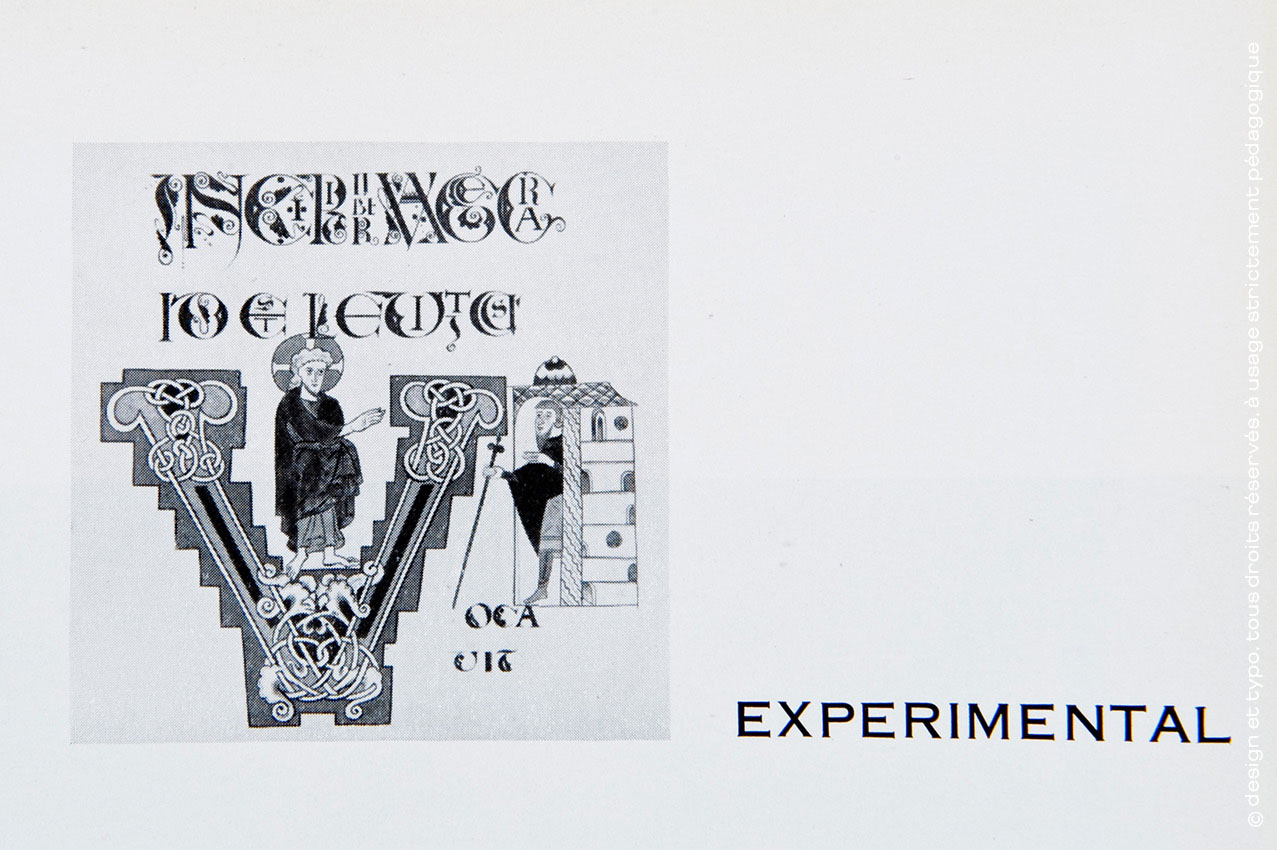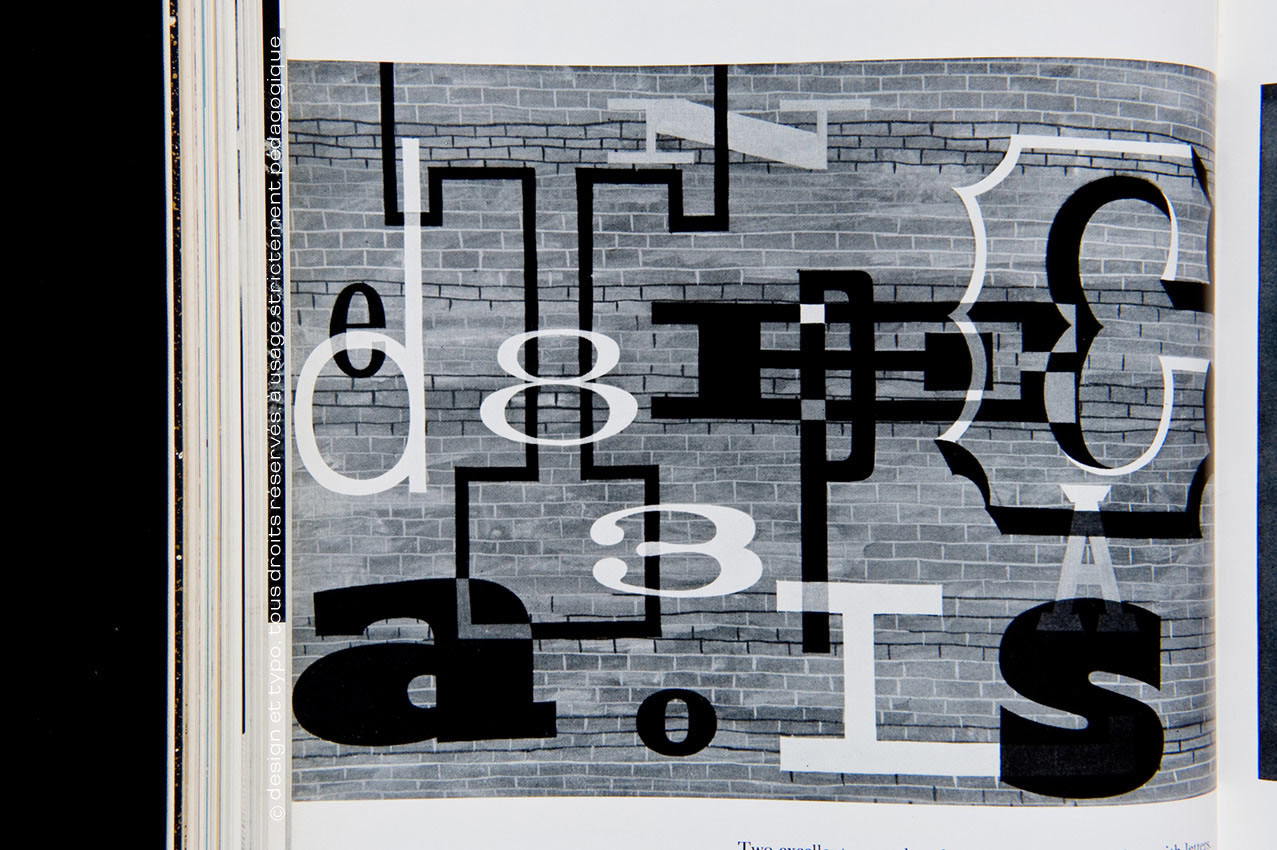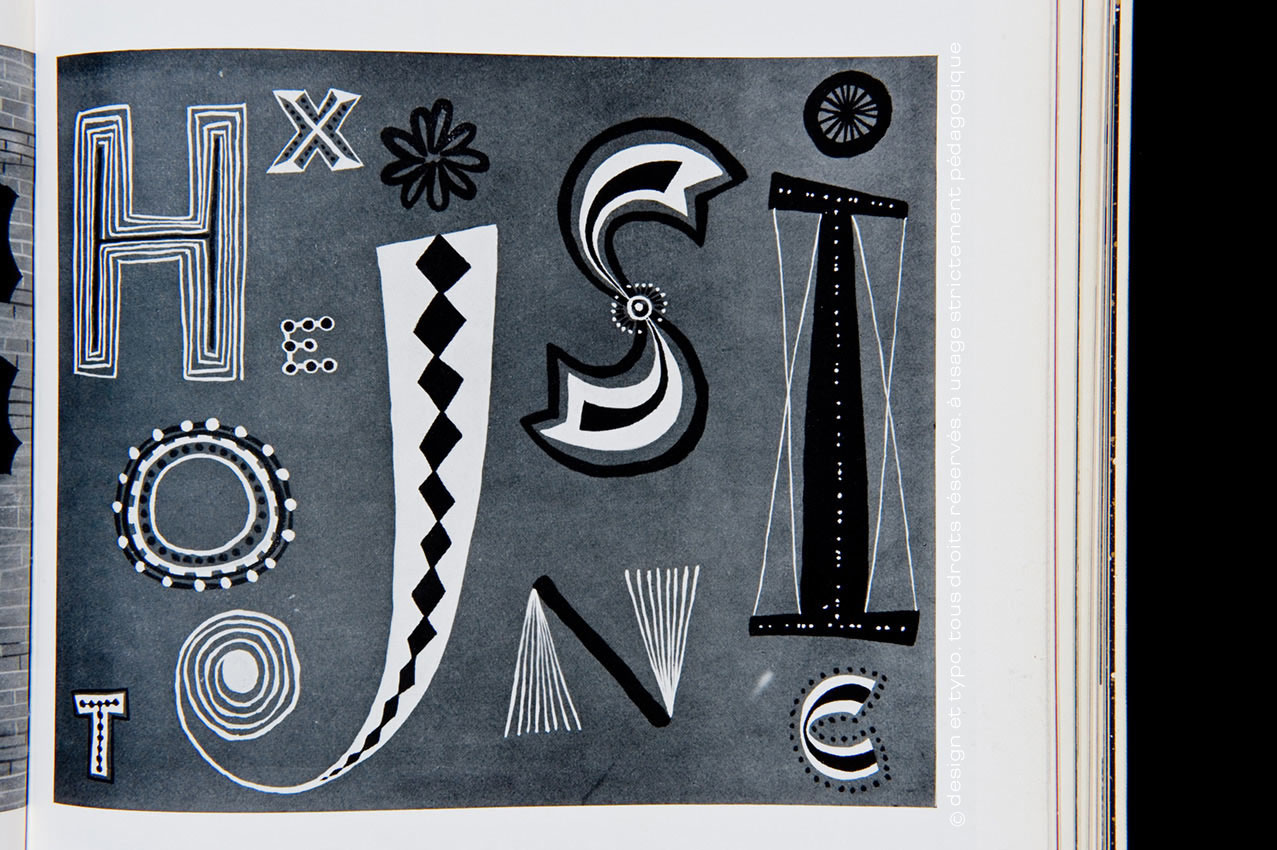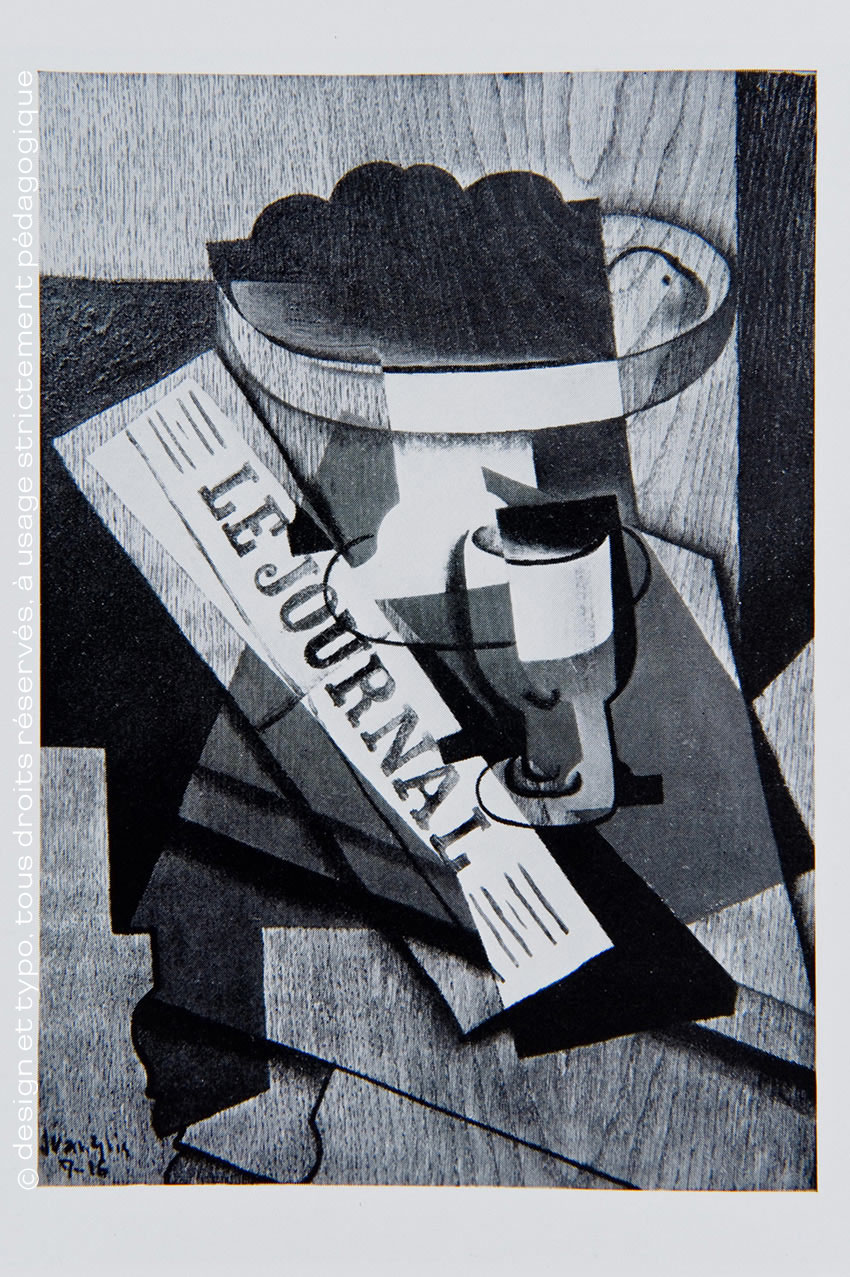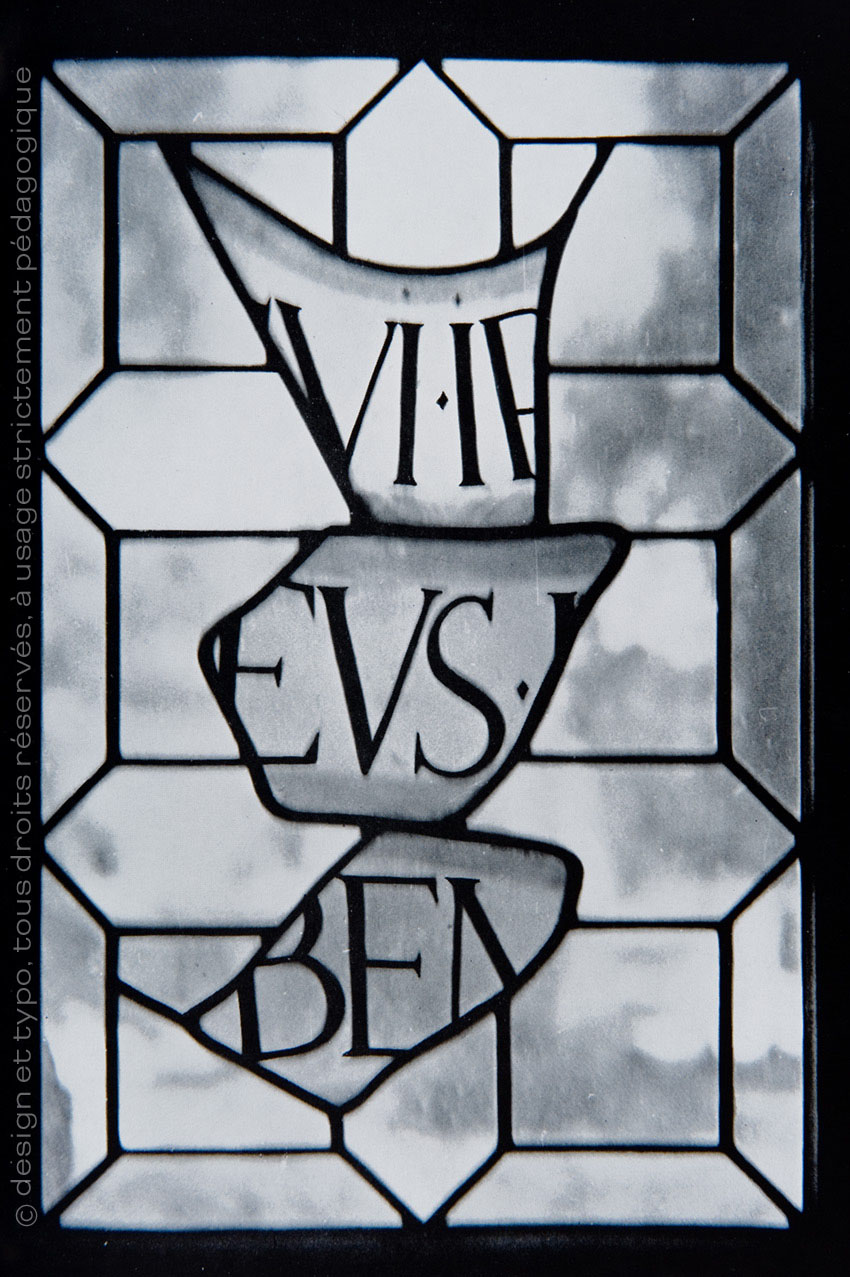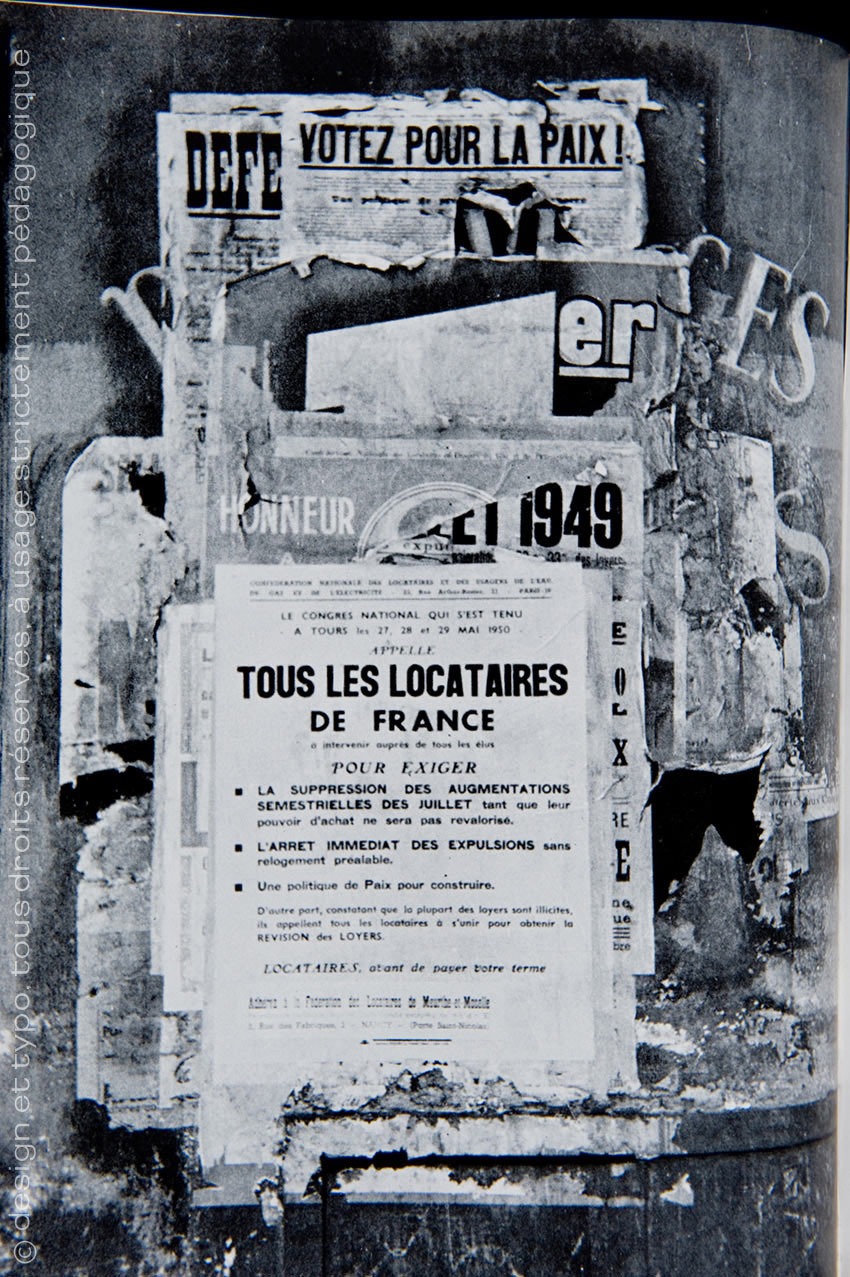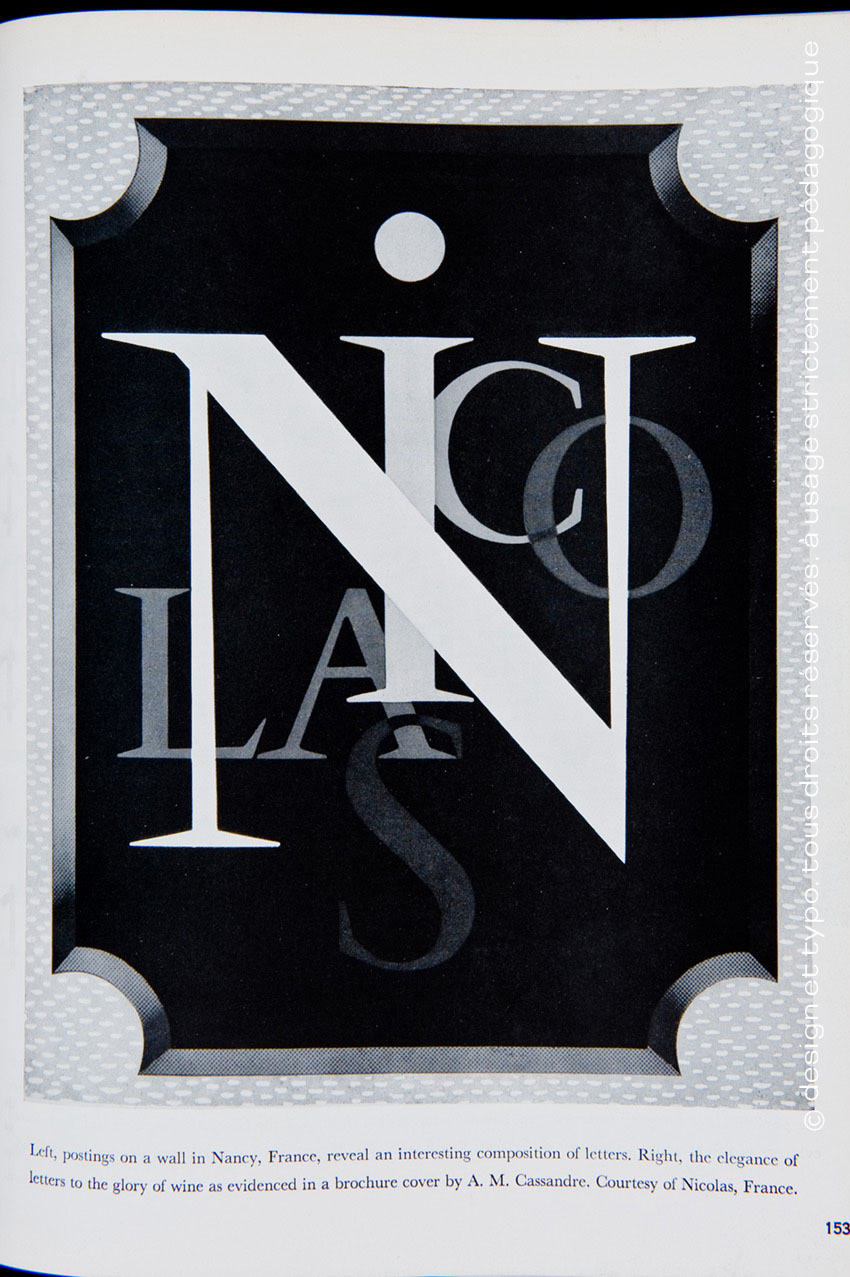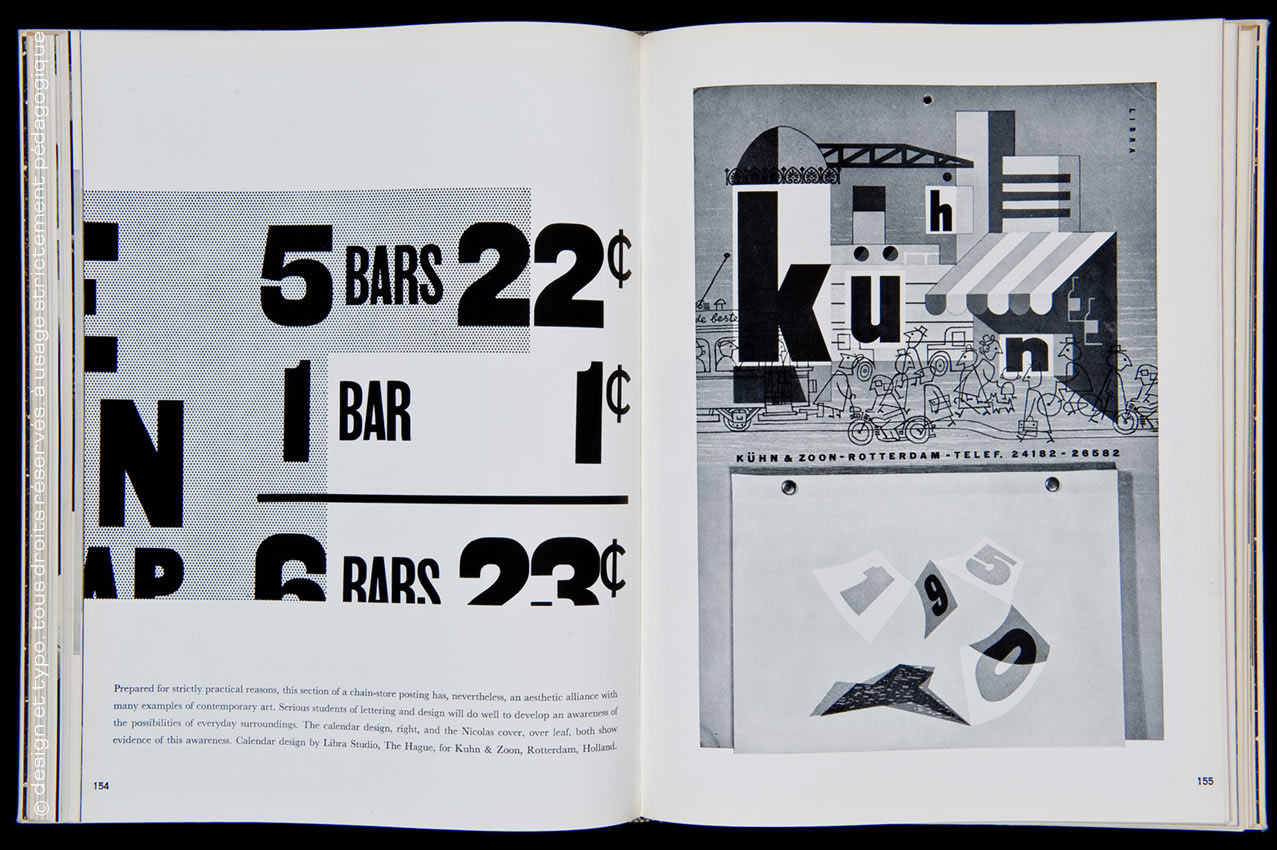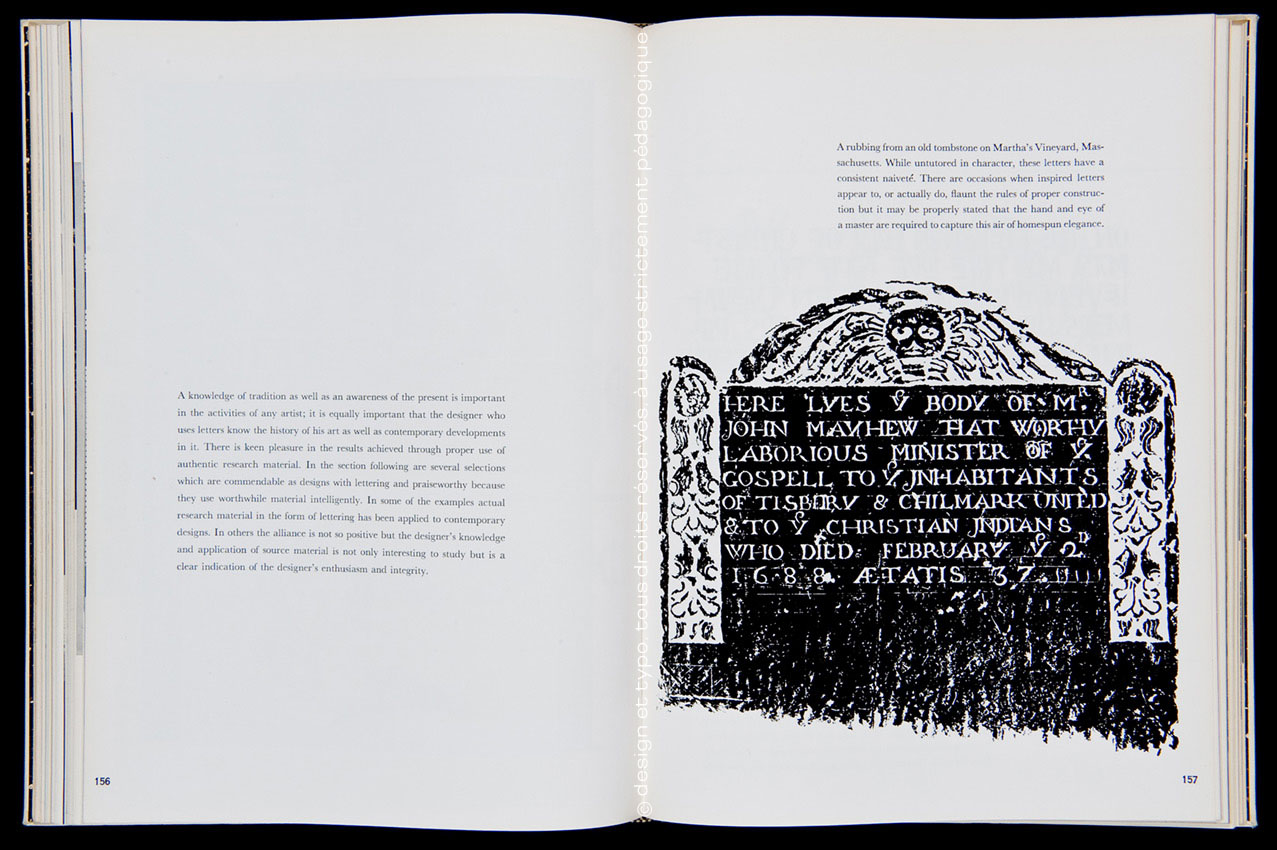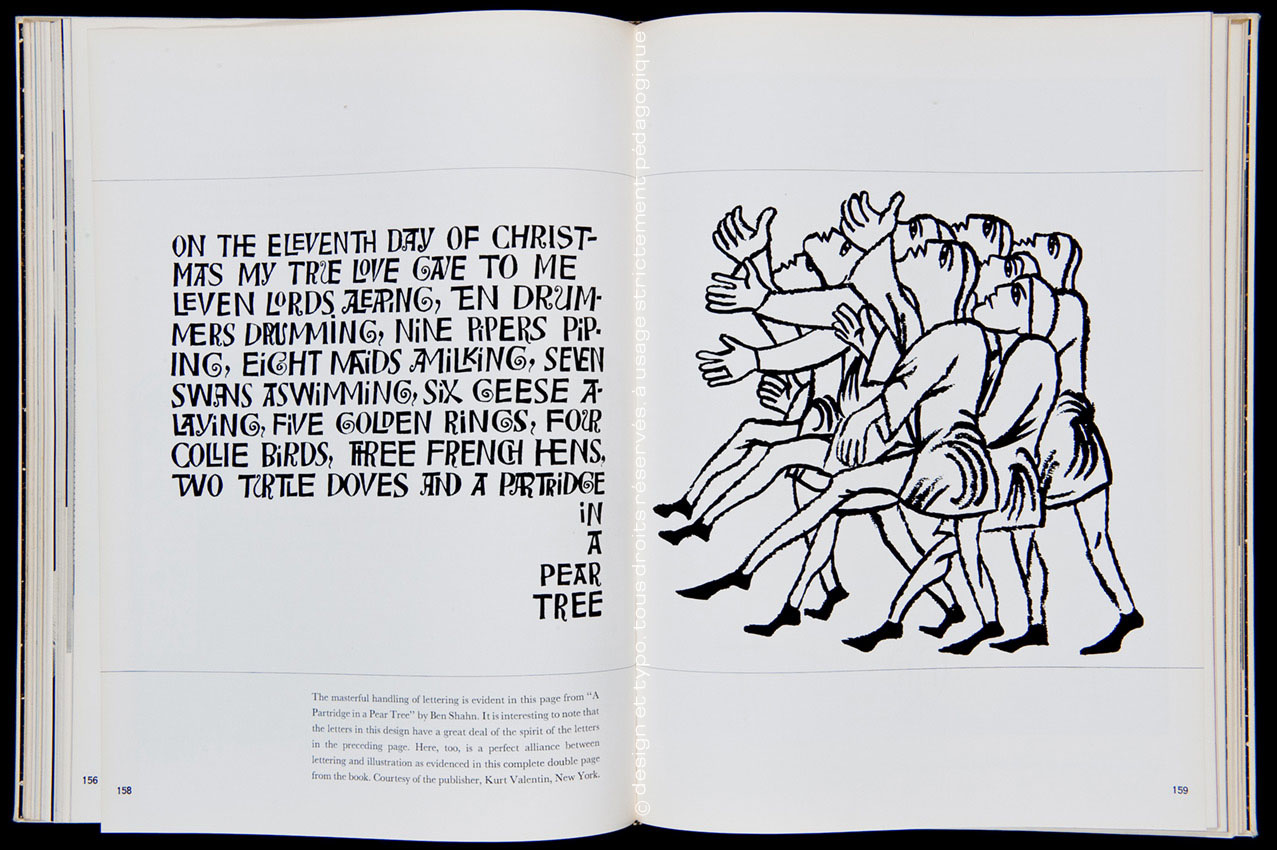
Typographie anglosaxonne et classification selon Raymond A.Ballinger (4/4)
Typography and classification by Raymond A.Ballinger (4/4)
Voici enfin le dernier chapitre de cet ouvrage de Raymond A.Ballinger.
À l’heure où nous apprenons le décès de l’une des plus grandes figures de la typographie américaine, Edward Rondthaler, qui nous a quitté à l’âge honorable de 104 ans de la maladie éternelle de la vieillesse… D’aucuns se souviennent de lui pour avoir lu son nom ici et là dans les chroniques de design et typo. Il avait fondé la première compagnie de phototitrage aux états-unis, Photolettering and Co. et participé activement à la création de ITC, International Typeface Corp avec Herb Lubalin et Aaron Burns.
Donc nous voici au dernier chapitre de Lettering Art in Modern Use de Raymond A.Ballinger qui aborde ici la typographie expérimentale des années 50. Expérimentale, mais aussi institutionnelle lorsqu’il photographie les packagings et l’architecture des grandes compagnies. La typographie est désormais présente sur toute la chaîne de la communication. Advertising, Packaging, Communication, Architecture et bien entendu et heureusement dans l’œuvre de plasticiens qui intégrent cet art dans leur pratique quotidienne.